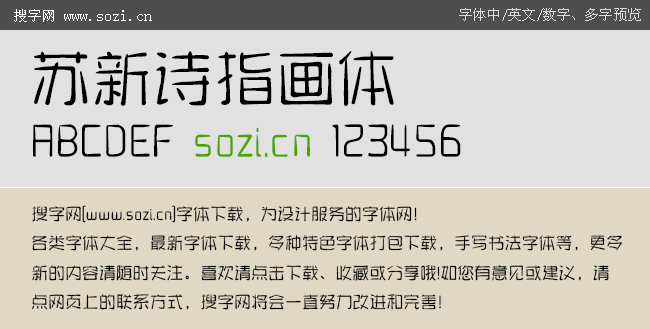
蘇新詩指畫體
搜字網(wǎng)提供一款蘇新詩指畫體中文字體下載,,該字體將筆畫處理的即圓潤(rùn)又尖銳,橫平豎直間造型類似于手指,筆鋒犀利,線條流暢,字形大方得體,適合應(yīng)用于廣告設(shè)計(jì)、名片設(shè)計(jì)、包裝印刷、產(chǎn)品設(shè)計(jì)等應(yīng)用。